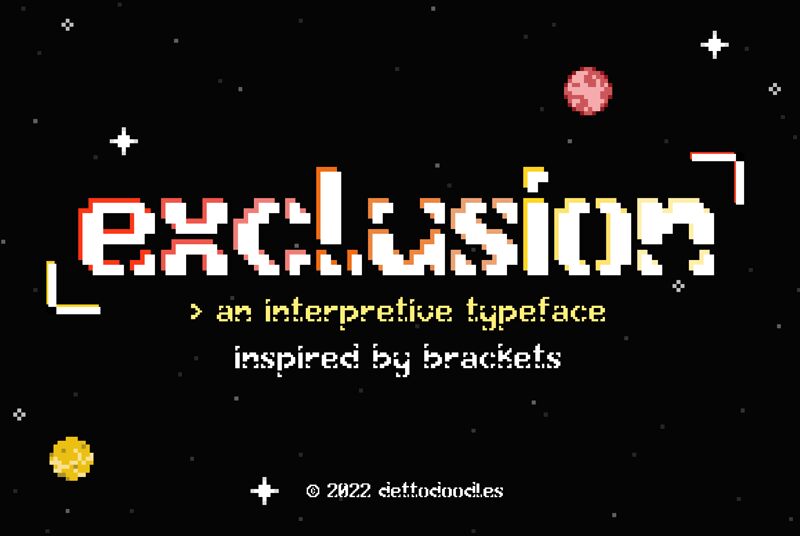
Exclusion di Emily Durandetto è un font bitmap gratuito dal ritmo spezzato, quasi «glitch». Le lettere sembrano scolpite in blocchi di pixel grossolani, con angoli a gradino e spaziature brusche che rendono il design volutamente frammentato piuttosto che semplicemente retro.
È ideale per titoli di poster, copertine di fanzine, menu di gioco, flyer per club e grafica web, dove un font gratuito può aggiungere una grinta digitale senza risultare troppo levigato. Poiché le forme si interrompono e si ricollegano in punti inaspettati, funziona benissimo anche per titoli brevi, schermate di presentazione e loghi che richiedono un carattere spezzato e a bassa risoluzione.
exclusion — Presentazione del carattere